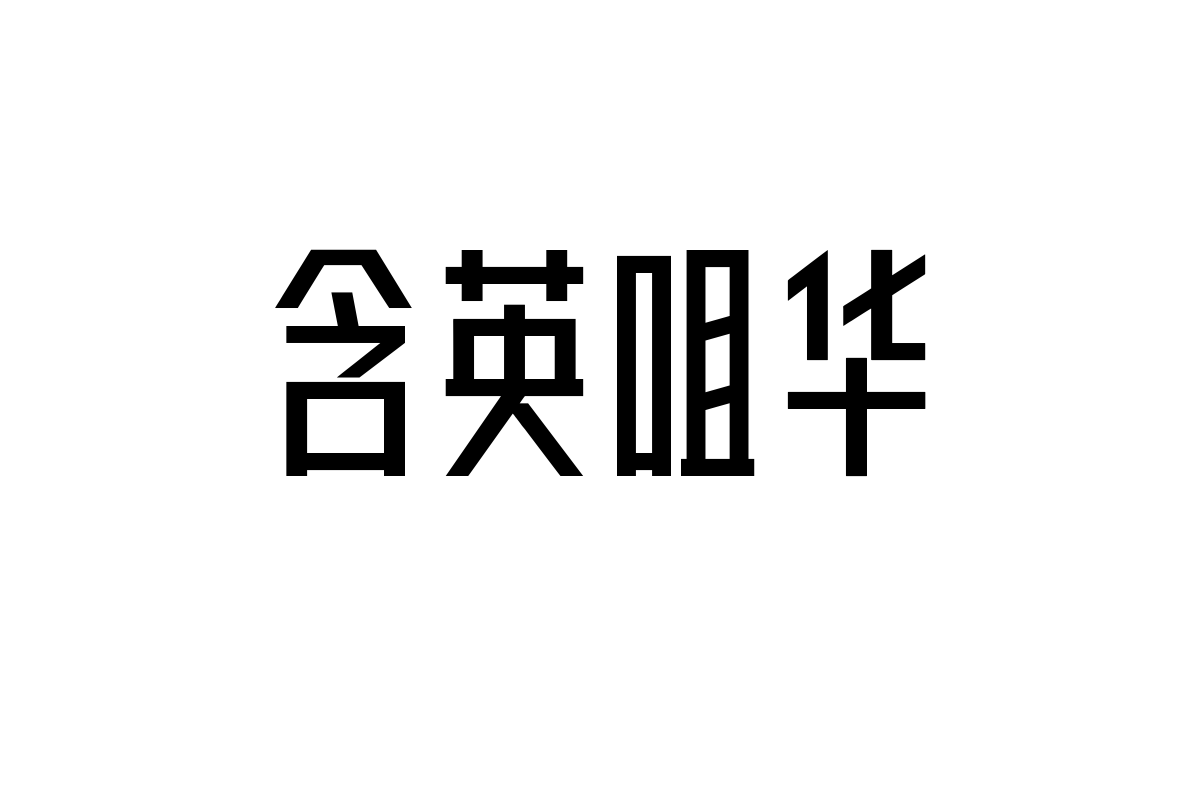
上首轩正体字体是一款具有独特风格的中文字体,其特点是笔画流畅、字形饱满、结构严谨。这种字体适用于需要展现庄重、大气氛围的场合,如商务报告、官方文件、广告设计等。
上首轩正体字体的特点如下:
1. 笔画流畅:该字体的笔画线条流畅自然,给人一种优雅的感觉。
2. 字形饱满:该字体的字形饱满饱满,给人以稳重的感觉。
3. 结构严谨:该字体的结构严谨,每个字的笔画都有明确的起止位置和方向,使得整个字体看起来整齐有序。
4. 适合正式场合:由于其庄重、大气的特点,上首轩正体字体非常适合用于正式场合,如商务报告、官方文件、广告设计等。
5. 可读性强:该字体在保持美观的同时,也兼顾了可读性,使得阅读起来更加舒适。
总之,上首轩正体字体是一款具有独特风格且适合正式场合使用的中文字体。